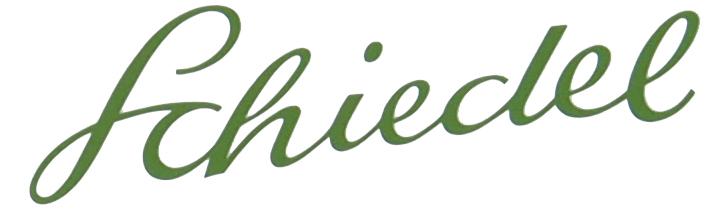
Geschwungene Schrift (Schiedel)
ich suche dieses Schrift,
bei whatthefont finde ich sie niht,
auch nicht, nachdem ich die nur jeden zweiten Buchstaben im Bild gelassen habe.
Könnt ihr mir bitte helfen?